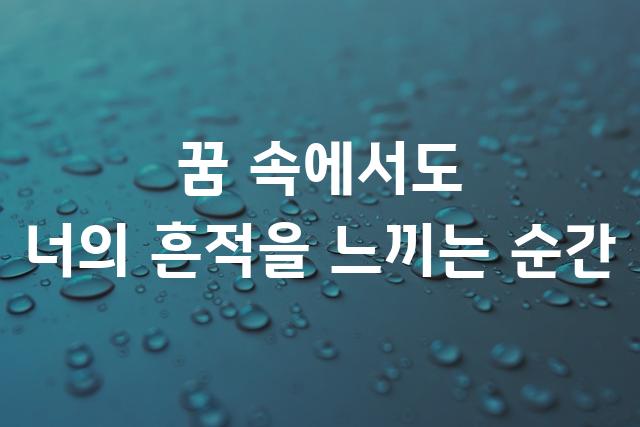
광양햇살체는 광양시청과 투게더그룹이 협력하여 제작한 기본 고딕 폰트입니다. 명료하고 깔끔한 느낌을 주며, 모던함과 전통적인 감성이 공존하는 디자인입니다.
광양햇살체은(는)
기본 고딕, 감성적인, 부드러움 계열의 생김새를 가지고 있으며
어린이 책, 인사말 카드, 카페 메뉴 등에서 자주 활용되며, 효과적인 메시지 전달에 적합합니다.
이 폰트는 음식/식음료, 라이프스타일, 유아/가족 분야에 잘 어울리며,
따뜻한, 친근한, 편안한 느낌을 담고 있는 것이 특징입니다.